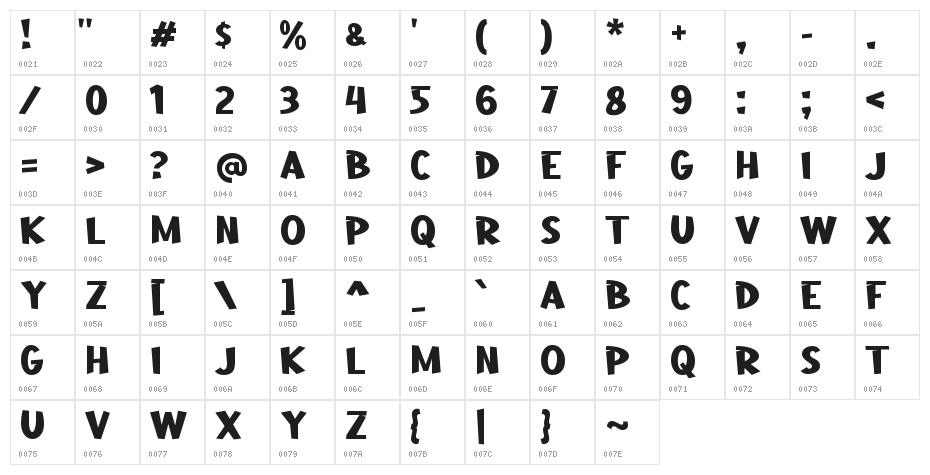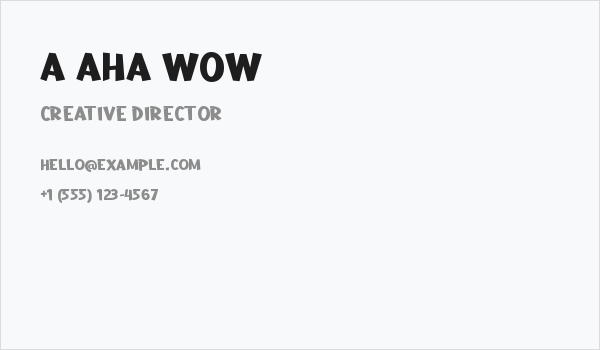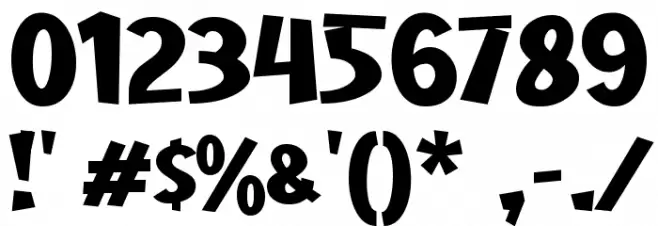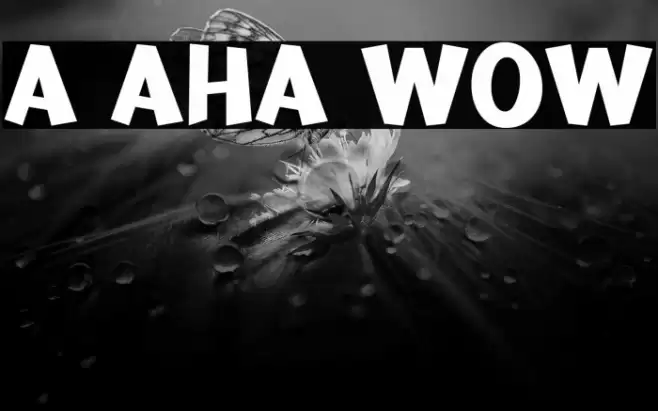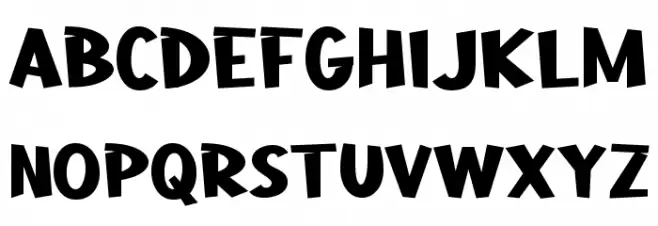
a Aha Wow Font
✎ Comic
| Gesamtstil | Playful, Cartoonish |
| Vorgeschlagene Projekte | Ideal for children's books, comic strips, playful branding, and eye-catching posters. |